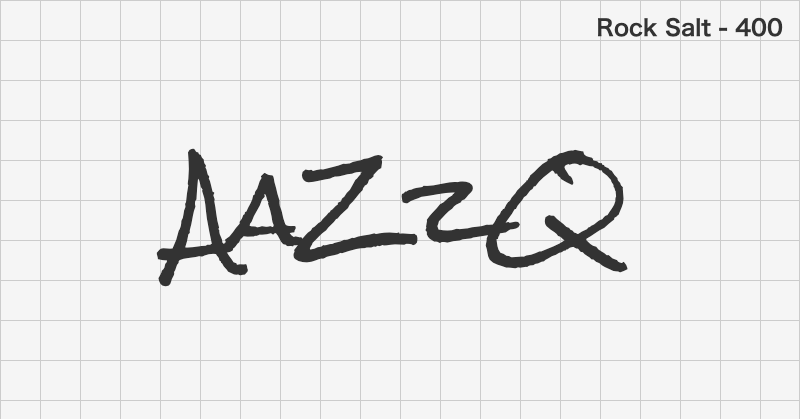
Rock Salt – 商用利用できる手書きフリーフォント
Rock Salt 手書きフォントの文字見本 (無料ダウンロード) 手書き
Rock Saltは、フェルトペンで手書きされたような個性的な印象を持つフォントです。プロジェクトに彩りを加えることができるユニークなデザインが特徴です。
Rock Salt は、Sideshow が手がけ、手書きの温かみを感じさせるフォントとして設計されました。個性的なスタイルを持ち、様々なプロジェクトでの使用を目的としています。